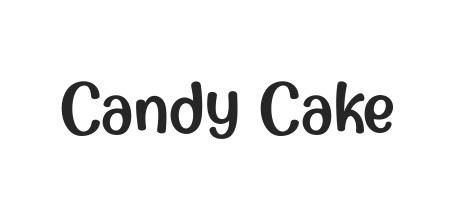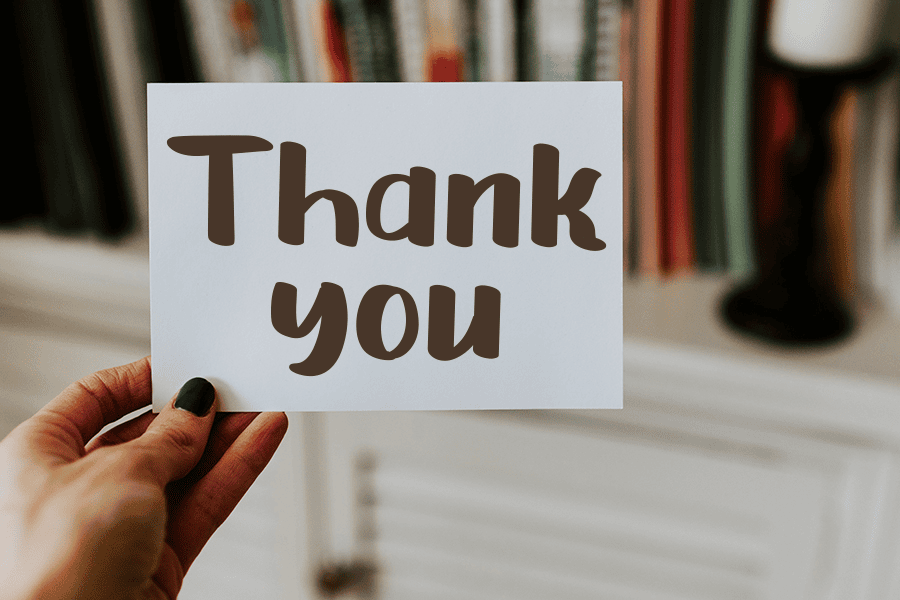
Nhiều designer gặp lỗi khi sử dụng Font Candy Cake Việt hóa do tình trạng thiếu dấu tiếng Việt hoặc các chi tiết bo tròn, họa tiết trang trí bị nhòe khi phóng lớn để in trên bao bì thực phẩm. Những lỗi kỹ thuật này khiến thiết kế mất đi vẻ vui tươi, ngọt ngào vốn có, làm giảm sức hút của sản phẩm và ảnh hưởng đến khả năng nhận diện thương hiệu.
Font Candy Cake là gì?
Font Candy Cake là phông chữ thuộc dòng Display với phong cách tròn trịa, đáng yêu, mô phỏng lại những viên kẹo ngọt đầy màu sắc. Điểm đặc trưng của bộ chữ này là các nét vẽ có độ bo tròn cao, tạo cảm giác gần gũi, vui nhộn và tràn đầy năng lượng. Đây là sự lựa chọn phù hợp cho các thiết kế nhãn mác bánh kẹo, đồ chơi trẻ em, bao bì mỹ phẩm thiên nhiên hoặc các poster sự kiện mùa hè.
Sự đáng yêu của font chữ giúp bao bì sản phẩm trở nên thu hút và để lại ấn tượng tốt với người tiêu dùng nhỏ tuổi. Tuy nhiên, bản gốc tiếng Anh thường không hỗ trợ bảng mã tiếng Việt. Bản tải font chữ candy việt hóa tại In Viva đã được xử lý kỹ thuật từng ký tự, đảm bảo dấu thanh và các ký tự đặc thù hiển thị cân đối, giúp designer thỏa sức sáng tạo trên mọi ấn phẩm truyền thông.
Lưu ý: Với font kẹo này, bạn nên phối hợp cùng các bảng màu rực rỡ như hồng, xanh lá, vàng chanh để làm nổi bật nét chữ vui nhộn trên bao bì.
5 ứng dụng Candy Cake Font Việt hóa trong thiết kế và in ấn
Nhờ phong cách chữ tròn trịa, vui tươi cùng các đường nét mềm mại mang cảm giác ngọt ngào, Candy Cake Font Việt hóa được ứng dụng linh hoạt trên nhiều sản phẩm bao bì, quà tặng và ấn phẩm thương hiệu hướng đến sự trẻ trung, gần gũi:
- Thiết kế bao bì bánh kẹo và thực phẩm trẻ em: Font Candy Cake phù hợp để thể hiện tên sản phẩm, logo hoặc slogan trên hộp bánh, túi kẹo, tem nhãn thực phẩm. Kiểu chữ đáng yêu giúp bao bì tạo cảm giác sinh động, thu hút sự chú ý của trẻ nhỏ và khách hàng.
- Sản xuất túi giấy và hộp quà tặng ngọt ngào: Khi kết hợp cùng giấy Ivory, Kraft hoặc giấy mỹ thuật, Font Candy Cake giúp các mẫu túi giấy, hộp quà bánh kẹo trở nên nổi bật, phù hợp với các sản phẩm quà tặng sinh nhật, lễ hội hoặc chương trình dành cho thiếu nhi.
- In ấn tem nhãn sticker sản phẩm handmade: Các nét chữ bo tròn của Font Candy Cake phù hợp để in trên sticker, nhãn dán hũ kẹo, chai nước hoặc sản phẩm thủ công, giúp thương hiệu tạo cảm giác thân thiện và dễ ghi nhớ.
- Thiết kế voucher, banner và ấn phẩm quảng cáo: Font chữ mang phong cách vui nhộn, phù hợp để sử dụng trên poster khuyến mãi, banner sự kiện hoặc các nội dung truyền thông dành cho ngành hàng thực phẩm, giải trí.
- Trang trí quà tặng dành cho trẻ em: Font Candy Cake có thể ứng dụng trên bình nước, áo thun, sổ tay hoặc phụ kiện cá nhân hóa bằng kỹ thuật in UV, in chuyển nhiệt, giúp sản phẩm trở nên độc đáo và mang dấu ấn riêng.
5 lưu ý khi sử dụng Candy Cake Font Việt hóa
Để Font Candy Cake Việt hóa giữ được vẻ đẹp mềm mại và đảm bảo độ sắc nét khi sản xuất thực tế, designer cần chú ý:
- Kiểm soát độ dày nét chữ khi in: Candy Cake có các đường cong bo tròn và chi tiết trang trí đặc trưng. Khi sử dụng trên tem nhãn nhỏ hoặc sản phẩm có diện tích in hạn chế, cần kiểm tra kích thước chữ để tránh tình trạng nét bị dính hoặc mất chi tiết.
- Tối ưu đường Path khi gia công bế nổi: Khi sử dụng Font Candy Cake làm logo trên hộp quà hoặc bao bì, các đường cong trong file vector cần được xử lý kỹ để khuôn dập nổi thể hiện rõ hình dạng chữ, hạn chế lỗi răng cưa hoặc biến dạng.
- Điều chỉnh khoảng cách ký tự (Kerning): Các ký tự có hình dạng tròn thường tạo cảm giác khoảng cách gần hơn thực tế. Designer nên cân chỉnh kerning để tên thương hiệu hoặc slogan có bố cục cân đối, dễ đọc.
- Lựa chọn màu sắc phù hợp: Font Candy Cake phù hợp với các gam màu tươi sáng như pastel, hồng, vàng hoặc xanh mint. Khi in thực tế nên kiểm tra hệ màu CMYK để đảm bảo thành phẩm giữ được sự nổi bật.
- Convert font trước khi gửi xưởng: Trước khi xuất file sản xuất, nên chuyển Font Candy Cake thành dạng vector bằng lệnh Create Outlines để hạn chế lỗi thiếu font hoặc thay đổi kiểu chữ khi mở file trên hệ thống khác.